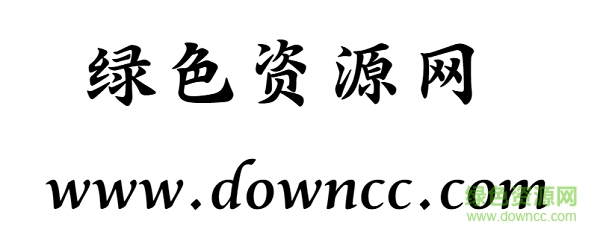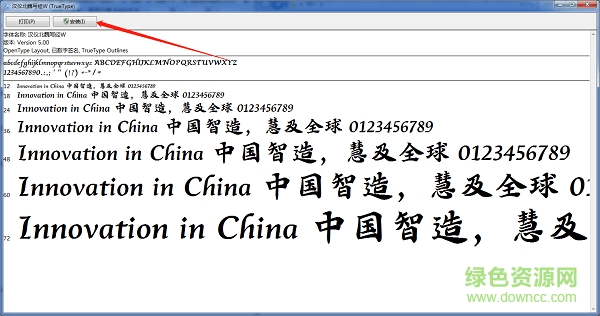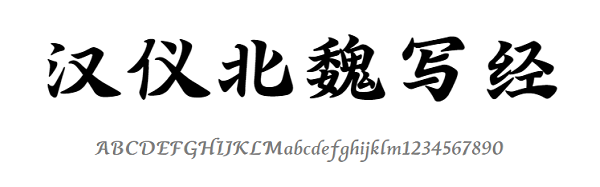
漢儀北魏寫經(jīng)字體是一款以北魏古風(fēng)字體為主要特色,通過書寫展現(xiàn)字體的古典,優(yōu)雅氣息,用于文章排版是會展現(xiàn)出浪漫唯美的形態(tài),給觀看者一種休閑的感覺,喜歡的用戶快來綠色資源網(wǎng)下載吧!
漢儀北魏寫經(jīng)w是一款中文字體,這款字體美觀大方、簡約干練,讓人有一種眼前一亮的感覺,適合應(yīng)用于藝術(shù)設(shè)計、平面宣傳設(shè)計、網(wǎng)頁設(shè)計、書法字帖等領(lǐng)域!